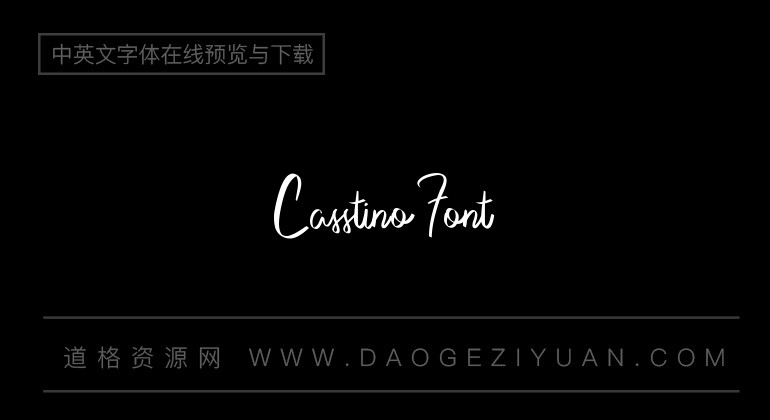
Casstino Font 是一款手写风格的英文字体,它具有非常独特的特点。Casstino Font 字体的特征在于其不规则的线条和形状,这种不规则的特点赋予了它一种温暖、自然和个性化的感觉。 Casstino Font 字体可以用于各种设计项目,例如海报、标志、印刷品、网站等,它的设计风格非常适合需要表达个性、温暖和自然感觉的项目。 Casstino Font 字体包含多种字形和字重,可以满足不同的设计需求。此外,它是一个完全免费的字体,可以自由下载和使用。内容介绍
Casstino Font是一款非常不错的手写艺术字体,具有很好的视觉感,适合于文化类的宣传设计、商业类品牌的广告和产品包装设计以及个性化文字排版等较多场景。